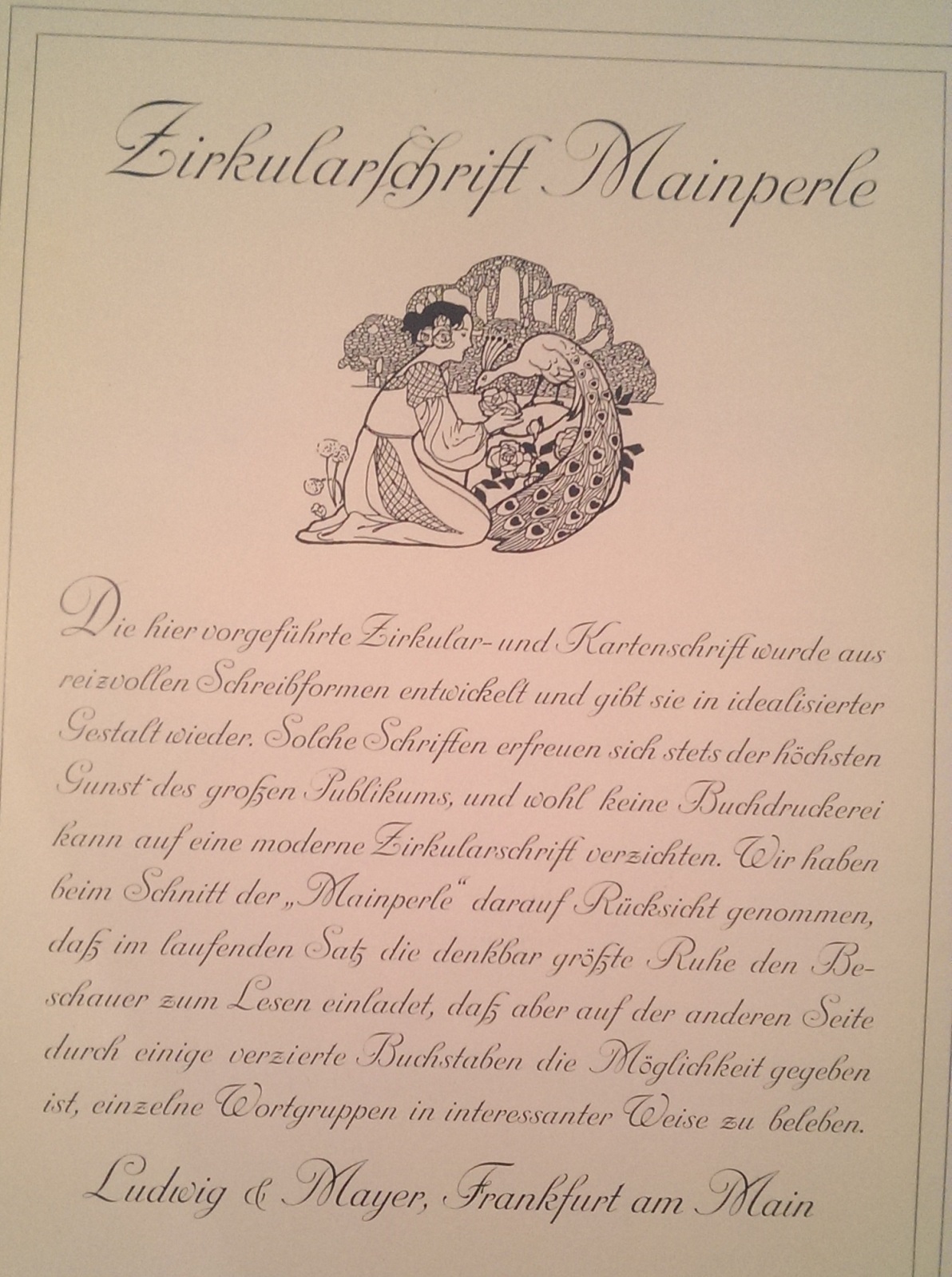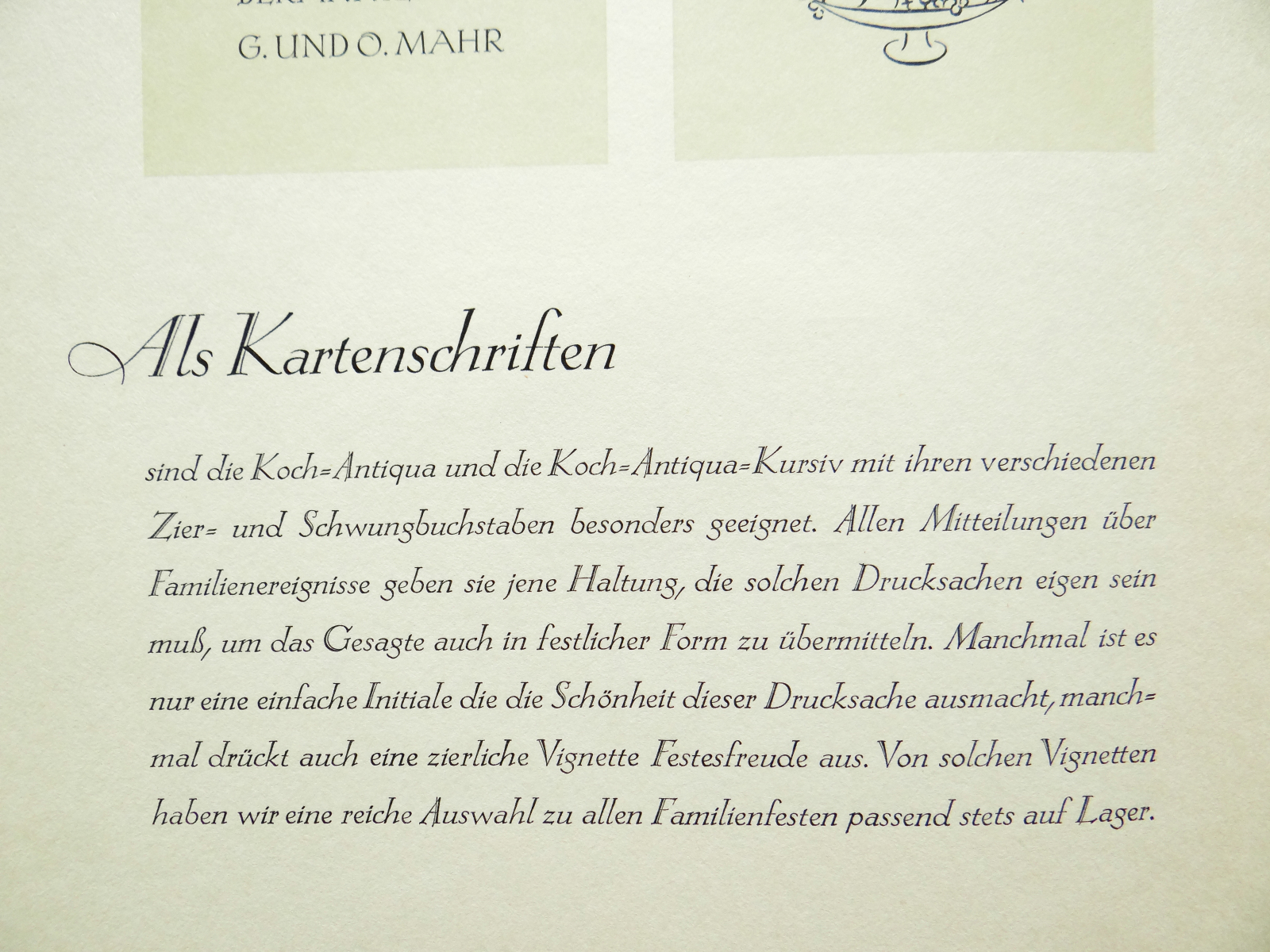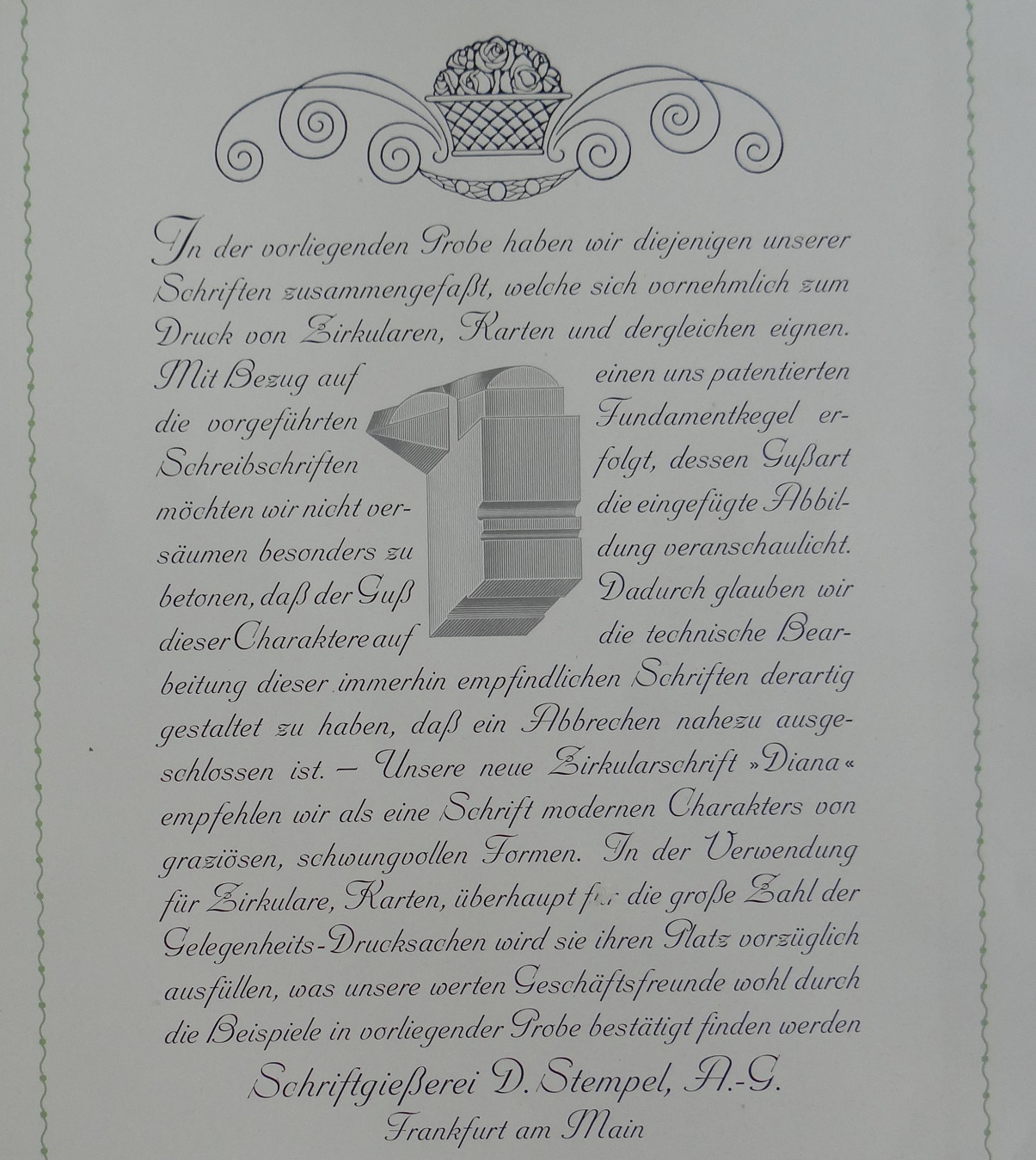
Definition Kartenschriften
Ich finde viele der mir bekannten "Kartenschriften" äußerst interessant und sehe sie als Bereicherung. Natürlich kann man auch alles mit den "Klassikern" setzen - aber warum sollte man das tun? Man verwendet ja auch nicht immer die gleichen Farben oder Papiere ...
Der Begriff Kartenschrift ist reine Marketingsprache, mehr steckt nicht dahinter.
Kartenschriften waren m. E. kein Marketing-Gag. Sie hatten zu Ihrer Zeit, im 19. und Anfang 20. Jh., durchaus Berechtigung und waren vom Auftraggeber gewünscht.
Wie in meinem Beitrag oben bereits angemerkt, wurden Karten jeglicher Art im Kupferstichdruck oder im Steindruck hergestellt. Das heißt, sämtliche Schriften wurden von Hand in die Platte graviert oder auf Stein lithografiert bzw. geschrieben – seitenverkehrt noch dazu. Hier entstanden eigene Schriften mit ganz persönlichem Stil, die sich zu den Buchdruckschriften z. T. stark unterschieden. Waren doch dem Buchdruck grafisch und technisch Grenzen gesetzt.
Höchste handwerkliche Präzision beherrschten diese Handwerker. Wir würden dies heute als Kunst bezeichnen.
Tiefdruck und Lithografie waren mit ihren grafischen Möglichkeiten auf diesem Gebiet dem Hochdruck überlegen.
Um nun diese hohe grafische Qualität zumindest ansatzweise zu erreichen, wurden eben diese Schriften als Vorbild für passende Bleilettern verwendet, um dann gesetzte Karten im Buchdruck herzustellen die dem Aussehen der beliebten Karten entsprachen. Auch konnte kostengünstiger für eine gesellschaftlich breitere Schicht produziert werden.
Man nahm sich bei der Herstellung der ersten Bleilettern ebenfalls ursprünglich die Schrift der alten handgeschriebenen Bücher als Vorbild und versuchte die hohe Qualität dieser Handschriften zu erreichen. Ähnlich ist das bei den Kartenschriften zu sehen.
Erwin hat noch den Gedanken eingeworfen, dass es sich um den Schriftstil von Landkarten drehen könnte.
Kann mich nicht erinnern, dass ich das geschrieben habe, aber ist nicht ganz von der Hand zu weisen.
Da auch Landkarten von Lithografen und Kupferstechern hergestellt wurden, ähneln diese Schriften den Kartenschriften oft sehr. Hatte doch diese Zunft ihren ganz eigenen Stil entwickelt.
Spricht man jedoch von Kartenschriften, ist nicht von Landkartenschriften die Rede.
Landkartenschriften würde man als „kartografische Schriften“ bezeichnen.
Da auch Landkarten von Lithografen und Kupferstechern hergestellt wurden, ähneln diese Schriften den Kartenschriften oft sehr. Hatte doch diese Zunft ihren ganz eigenen Stil entwickelt.
Ja, so hatte ich das herausgelesen. Aber stimmt, steht so nicht wörtlich im Originalbeitrag.
Anfangs war es sicherlich so, daß die Kartenschriften den gestochenen Schnörkel imitierten. Aber die Industria und die Monument von Gursch sind eben auch sog. Kartenschriften. Oder meine Fedora oder Feodora. Diese Entwicklung müßte man in einer Definition berücksichtigen.
Zur Definition gehört sicherlich auch die Menge. Kartenschriften waren kleine Sätze, die oft in eigenen Schatullen geliefert wurden. Viel verkauft wurde davon sicherlich nicht. Ich habe bei den zahlreichen Druckereiauflösungen in den letzten 20 Jahren fast nichts gefunden, das aus den o.g. Katalogen stammt. Und die Größe dürfte auch dazugehören, Kartenschriften sind nicht in sehr großen Graden erhältlich gewesen, meistens nur bis Mittel oder Tertia, also 14 und 16 Punkt. Schatullen und Sonderkästen sind beim Setzer unbeliebt, weil das Setzen und Ablegen viel länger dauert als aus dem normalen Kasten und weil sie immer im Wege stehen. Ich habe mehrere solcher Kartenschriften, die ich aus diesen Gründen gar nicht benutze. In der Druckerei, in der ich als Akzidenzer angestellt war, hatte der Meister ein oder zwei Kartenschriften in größeren Mengen gekauft und in normale Kästen gelegt, damit die Arbeit rationell blieb. Mimosa. Geburtsanzeigen, Einladungen, Visitkarten.
Wenn es um »besonders gut für Akzidenzen« gegangen sein soll, hätte man ja auch »Akzidenzschriften« sagen können.
Vielleicht war das so eine zeittypische Fremdwort-Ersetzungs-Geschichte. Heute kann ja außerhalb des graphischen Gewerbes kaum noch jemand was mit dem Begriff »Akzidenz« anfangen (weswegen es auch sicher nicht hilfreich wäre, wenn ich meinen Betrieb »Akzidenzdruckerei« nennen würde). Vielleicht war das damals nicht viel anders.
Unwahrscheinlich, glaube ich, denn den lateinischen Begriff gibt es ja schon – tja, weiß ich gar nicht, wie lange. Wie lange eigentlich? Aber die Ableitung von accidit sicherlich aus Zeiten, als die Drucker noch Lateinisch setzten. Und die Herkunft des scherzhaften Begriffs »Akzidenzier« für den Akzidenzsetzer würde ich vor 1930 vermuten.